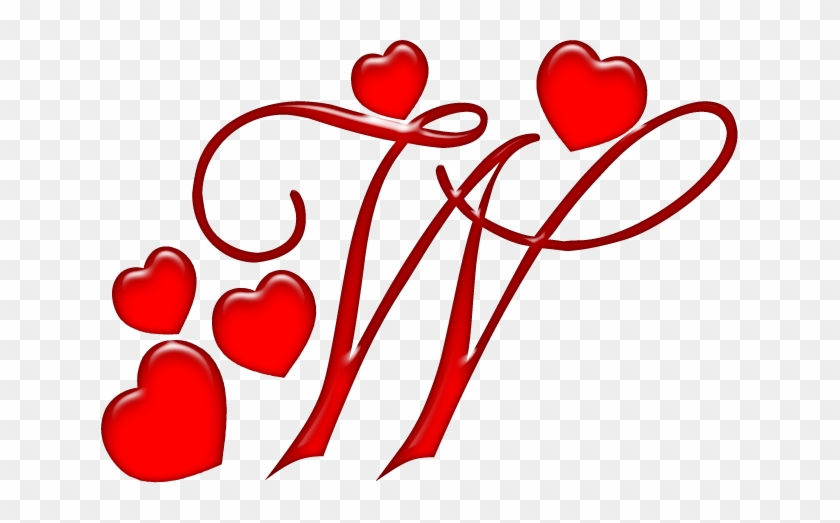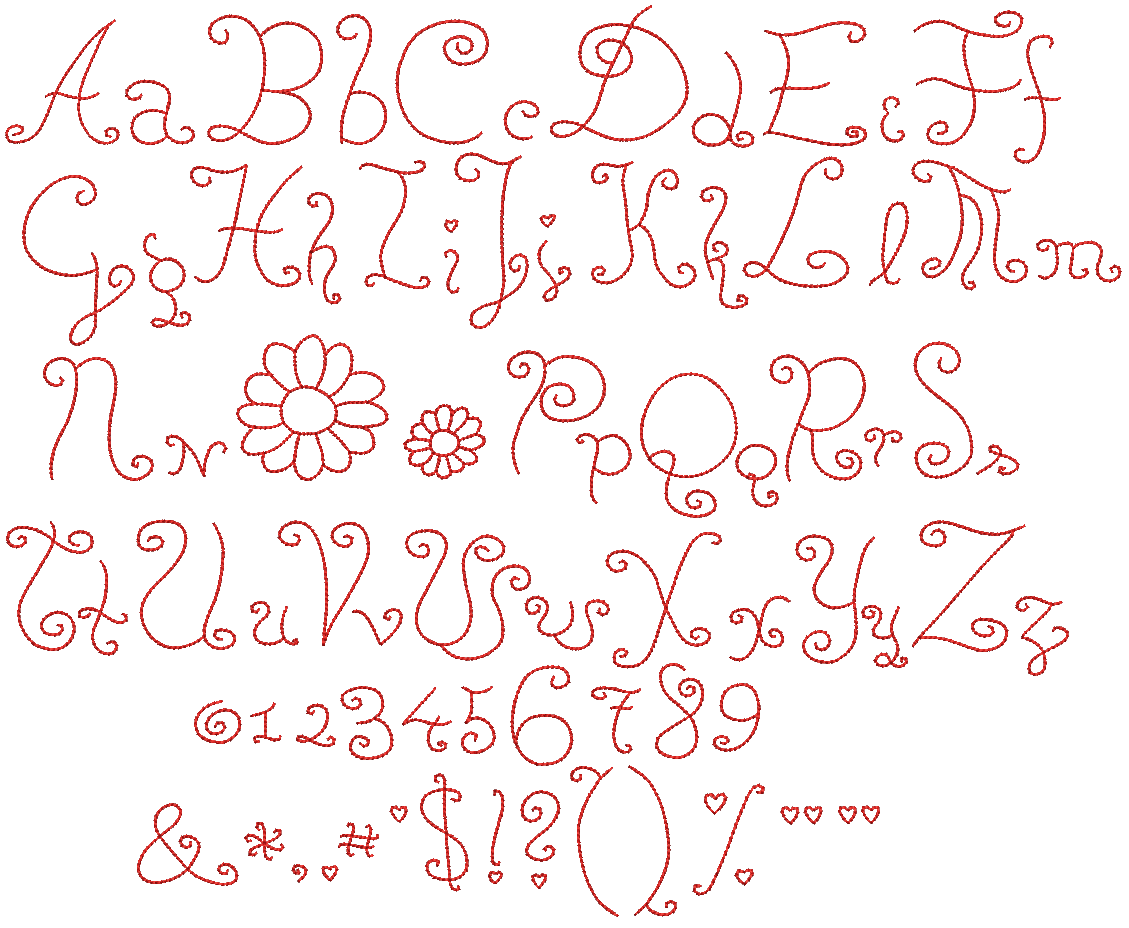
Романтические кисти, шрифты, вектор, иконки про любовь и не только
Хотел опубликовать подборку разных романтических дизайнерских материалов перед днем святого Валентина, но немного не успел. Поэтому сможете использовать их через только год либо найдете кое-что полезное к приближающемуся 8-му марта (там могут пригодиться те же сердечки, романтические шритфы с фонами и т.п.). Кстати, в блоге уже были посты по схожей тематике, вы могли видеть красивые обои ко дню святого Валентина а также наборы кисти розы для Photoshop. Сегодня же по аналогии с постом про хэллоуин собрал разные материалы: от вектора до иконок. Скачать их сможете, перейдя по соответствующим ссылкам в картинках.
Романтические шрифты
В принципе, достаточно часто под романтическими шрифтами подразумеваются просто красивые каллиграфические рукописные варианты, которые грамотно используются совместно с другими объектами в дизайне. Хотя некоторые шрифты все же имеют отличительные «любовные» мотивы.
Words Of Love
Janda Romantic
Romantic
Little Lord Fontleroy
Love Letters Font
Love & Trust
ForgetMeNot
La Belle Aurore Font
Jane Austen
Volstead
Magnolia
MyValentinesLove
Надеюсь, некоторые материалы вам пригодятся в работе. Постарался подобрать действительно лучшие бесплатные наборы кистей сердечек, романтических шрифтов и вектора, а также иконок по тематике любви. Из всего этого могут получиться достаточно неплохие тематические открытки и иллюстрации.
- Далее в поле, расположенном слева страницы, необходимо выбрать наиболее подходящий шрифт и скопировать его название. Подтверждать свой выбор кнопкой «Ок» необязательно.